Interview mit Uwe Loesch
Anlässlich der Ausstellung „Hans Hillmann. HaltMale – vom Plakat zum Bildroman“, die vom 17. April bis zum 12. Juni 2005 im Klingspor-Museum in Offenbach zu sehen war, besuchte Uwe Loesch, Professur für Kommunikationsdesign an der Bergischen Universität Wuppertal, mit seiner Klasse das Museum, um mit Hans Hillmann im Gespräch durch die Ausstellung zu führen. Anschließend wurde er von uns im Vorhof des Museums interviewt.
Herr Loesch, wenn man in Ihren Plakaten die Kombination von Schrift und Bild mit der Herangehensweise von Hans Hillmann vergleicht, dann hat es den Anschein, als ob Hillmann sehr oft die Schrift dem Bild angepasst hat oder gar selbst als Bildteil integriert, während bei Ihren Plakatentwürfen die Schrift mehr auf das Motiv eingeht und Sie Bild und Schrift meist in Kontrast setzen, so dass eine Spannung zwischen beiden Komponenten entsteht?
Das ist ein Aussagesatz und keine Frage. Deshalb könnte ich jetzt einfach nur „Ja!“ sagen. Hans Hillmann war als Plakatgestalter seiner Zeit weit voraus! Beispielsweise zeigt sein Plakat „Pierre und Paul“ eine Art von Eckfeldtypografie, die er damals häufiger verwendete. Hillmann räumt ein. Er macht Platz für die Typografie. Andererseits lässt er seine Illustration ein wenig über den Text laufen und macht so eine zweite Bildebene auf. Was auf den ersten Blick etwas eingeengt in der Ecke steht, ist eben doch schon wieder gut. Beschäftigt man sich intensiver mit der typografischen Gestaltung seiner Plakate, dann muss man erkennen, dass er äußerst subtile und immer wieder neue Konzepte ausprobiert oder ganz einfache Lösungen bevorzugt. Viele seiner frühen Plakate sind heute noch uneingeschränkt gültig.
Das Verunglückte, das zum Gestaltungsprinzip erhoben werden kann, war ihm seinerzeit sicherlich eher fremd. Wenn wir uns beispielsweise an der Tür dort die Typografie der Öffnungszeiten des Museums anschauen, dann haben wir so ein Beispiel von Glück im Unglück: Bürgerliche Mittelachse hinter schmiedeeisernen Dekorationsansprüchen. Die Wehrhaftigkeit der Tür wird zum Ornament. Die Typo hängt hier wie eine Klunker am Ohr des Zeitgeistes.
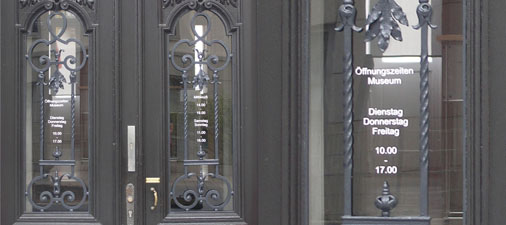
Man möchte sofort ausprobieren, wie die Typo linksbündig hinter Gittern ausschauen würde. Wer am Computer arbeitet, denkt in mehreren Ebenen und weiß, dass Text Bild und Bild Text sein kann. Und dass wir Text und Bild tauschen oder beliebig viele Text-Bild-Ebenen aufmachen können. Und das konnte man Anno dazumal alles nicht. Also hat man es auch nicht gedacht.
Nun gibt es ja heutzutage wieder diese Tendenzen, bei denen man von einer „gewollten Formlosigkeit“ sprechen kann, wo der Text bei Plakatentwürfen wieder scheinbar gedankenlos in die Ecken gesetzt wird.
Ja, das ist natürlich die allergrößte Kunst! Weil es am Computer schwierig ist, etwas so zu gestalten, dass es aussieht, als habe man es nicht gestalten wollen oder als habe man es gar nicht gestaltet, sondern der Zufall als unbedingter Reflex einer reaktionären Maus hatte die Hand im Spiel. Ich mache so etwas manchmal heute noch mit Hammer und Sichel. Beispielsweise schneide ich Typographie aus und werfe sie einfach auf das Format, um zu schauen, was daraus wird.
Meinen Sie da Ihre „Fünfminutenplakate“?
Meine Fünfminutenplakate sind Ergebnisse einer spontanen Idee. Anschließend probiere ich alle möglichen Alternativen, um dann am Ende, wenn ich Glück habe, festzustellen, dass die erste, spontane Idee wirklich die beste war. Wenn ich diesen Prozess aber überspringe, traue ich meinem Plakat nicht über den Weg. Es gibt von mir solche spontanen Plakate, die ich einfach drucken ließ. Zum Beispiel das Plakat NEWS für EBVscan. Es zeigt viele Bilder von Fernsehsendungen, die ich eine Nacht lang im YMCA von New York mit einer Polaroidkamera abfotografierte. Zurück in Deutschland, legte ich die Bilder einfach planlos im Nebeneinander auf dem Fußboden aus. Zufälligerweise ergab sich ein Schachbrettmuster. Diese Musterhaftigkeit, die wir exakter schon in römischen Mosaiken vorfinden, wurde von mir unter Vermeidung des rechten Winkels übernommen.
Solche Entscheidungen passieren dann aber nicht aus Termindruck?
Nein. Manchmal hat man einfach keine Lust, anstrengende Konzepte zu entwickeln. Ich glaube auch, dass wir neue Gestaltungsprinzipien meistens per Zufall entdecken. Mir geht das jedenfalls so.
Beim Spielen?
Im Computer ist es ja vor allem der ständige Unfall, der inspiriert. Irgendetwas flippt weg. Und dann macht man Screenshots und baut alles wieder mühevoll nach, was man mit der Maus gerade festhält. Beispielsweise fotografierten wir mal einen ganzen Kalender vom Monitor ab. Wir beschafften uns das Programm eines Bildschirmschoners und fütterten den Computer mit Format füllenden Monatsziffern und den Kalendarien. Der anschließende Auflösungsprozess wurde mit einer Kamera festgehalten und anschließend rekonstruiert. Der Kalender ist übrigens richtig gut geworden, obwohl er als Datengeber kaum zu gebrauchen war und auch nicht gebraucht werden wollte.
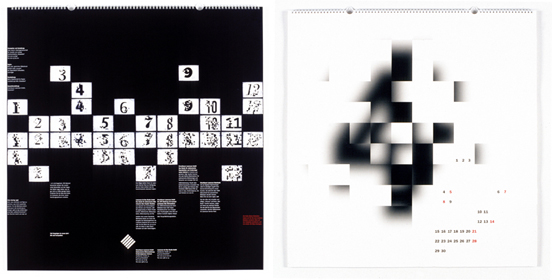
Gehen Sie denn als Typograph, gerade bei der Plakatgestaltung, zuerst mit einer Textidee an die Arbeit? Es gibt doch viele Plakate von Ihnen, die nur mit Text funktionieren.
Ich überprüfe eigentlich regelmäßig, ob ich die Bildidee nicht weglassen kann. Ich glaube ohnehin, dass das Bild im Kopf stärker ist, als das Abbild. Allerdings gibt es auch fantastische nonverbale Plakate, die nur mittels Bild kommunizieren. Heutzutage kann man ja ganz schnell testen, wie das ganze Teil ohne Bild aussieht. Und meistens ist das reizvoller.
Andererseits gewinnen viele fotografische Arbeiten erst an Bedeutung, wenn man sie mit Typographie in Verbindung bringt und eine Wechselbeziehung zwischen Text und Bild herstellt.
Ich freue mich sehr über das Interview. Es unterstreicht, dass hinter den eigenwilligen und markanten Typo-Plakaten, die das Klingspor Museum seit 2002 annoncieren (könnten einige hier als Abbildung ergänzt werden?), jemand mit lebendigen Überlegungen zu Typografie steckt. Jemand, der mit seiner avancierten Hinterfragung des Regel- und Erwartungsgemäßen Anstösse gibt und dabei Prägnanz und Identität entwickelt. – Mein großer Respekt gilt “typeoff” und dem Stammtisch für Typografie, an dem sich gedankenreich mit Schrifterscheinung auseinandergesetzt wird. Bitte immer wieder auch im Klingspor Museum!